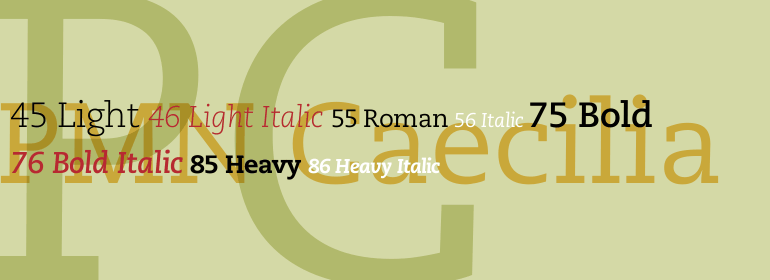
PMN Caecilia®
PMN Caecilia®,这款字体结构工整、笔画清晰,兼顾美观与易读性,适用于标题、正文、海报、包装、LOGO 等多种场景。字形优雅稳定,风格百搭耐看,适配日常排版与创意设计,让文字呈现更舒适、更具质感。PMN Caecilia®一笔一画,皆是细节,以均衡的比例、流畅的线条打造舒适视觉体验,字形端正大气,风格简约现代。无论是商业设计、品牌宣传还是日常排版,都能轻松驾驭,让文字更有格调与力量。PMN Caecilia®字体下载。
字体品牌: Monotype 设计师:Noordzij,Peter Matthias 字体分类:衬线体 字体属性:外文 字符集:Unicode 发布时间: 2018